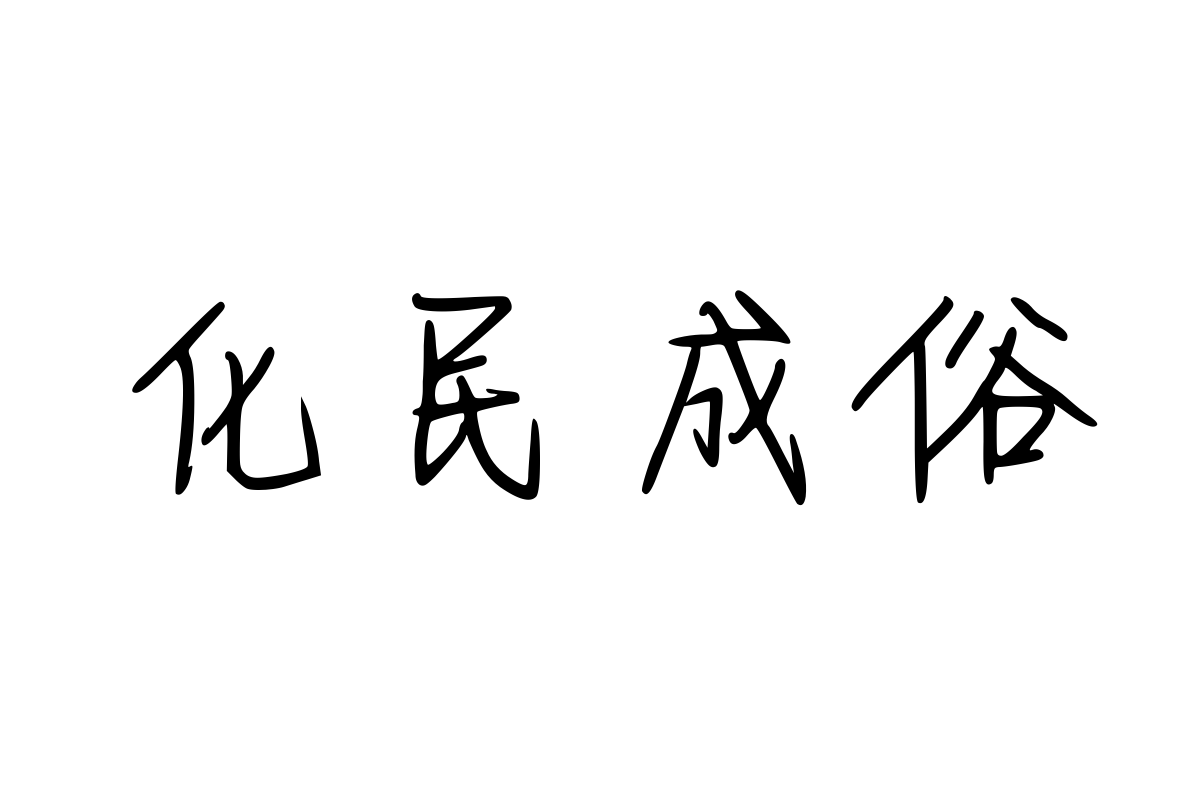
思雨君问归期是一款字体,由上海云字库科技有限公司开发。这款字体以其独特的设计风格和优雅的线条而受到广泛赞誉。它采用了传统的书法风格,将汉字的笔画进行了简化和美化,使得每个字都显得更加流畅和优雅。同时,这款字体还融入了现代的元素,使得整体风格更加时尚和现代。无论是用于设计海报、广告还是其他宣传材料,思雨君问归期都能为作品增添一份独特的魅力。